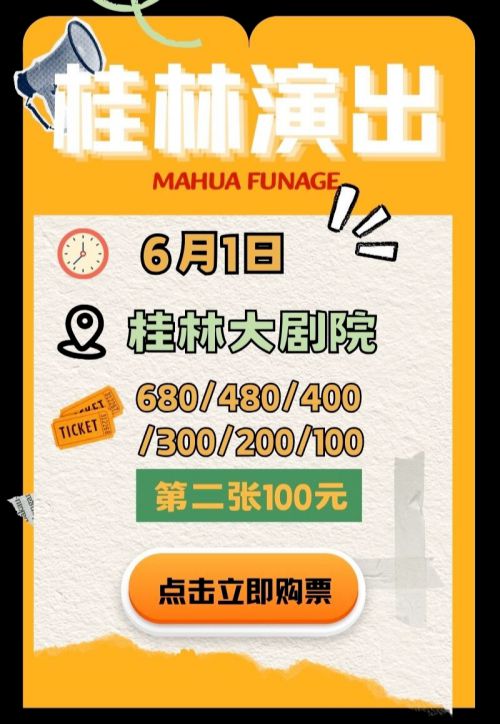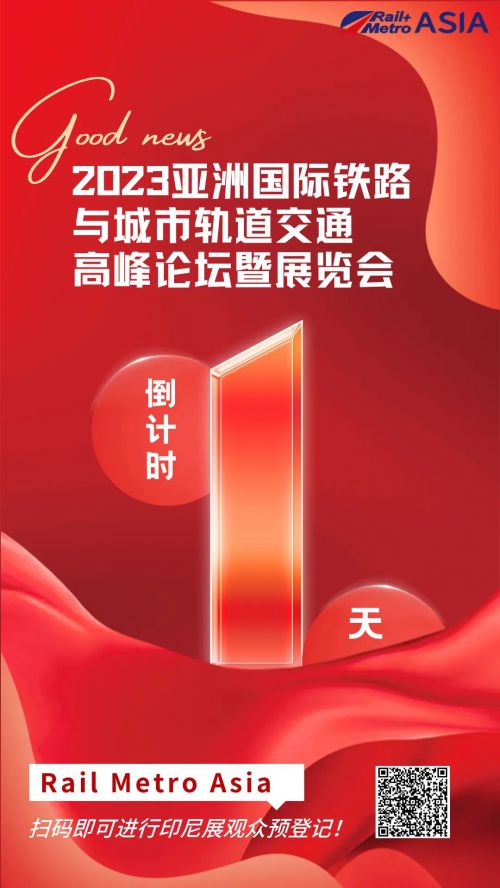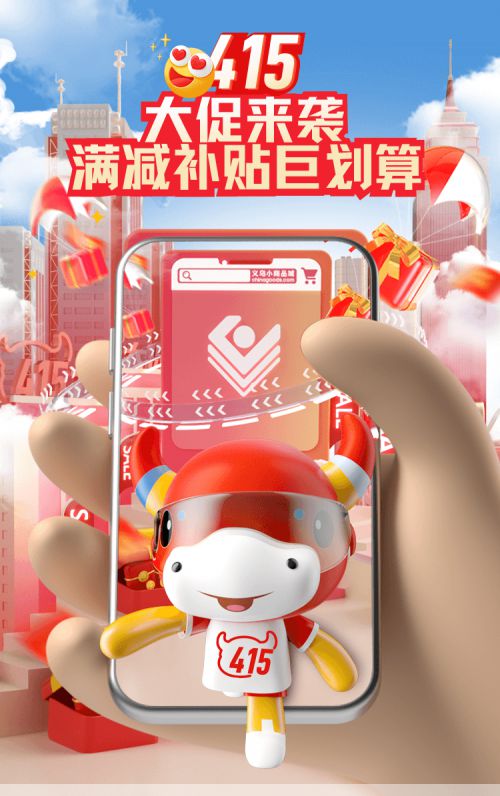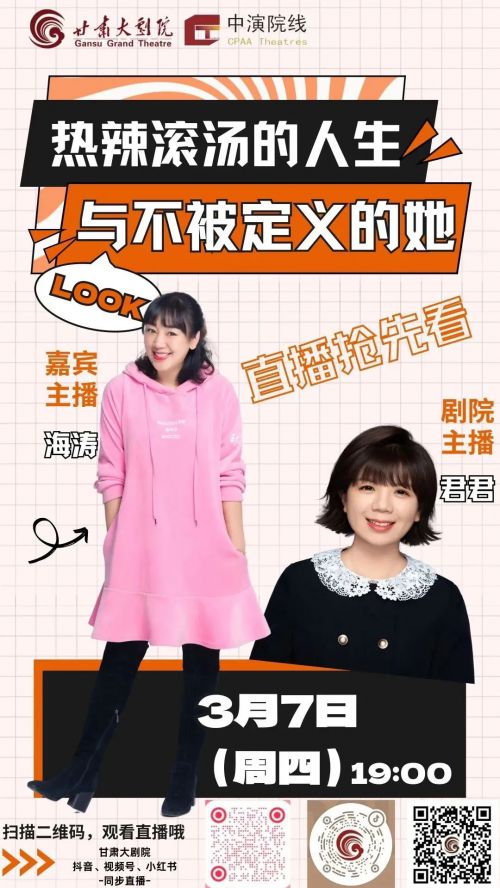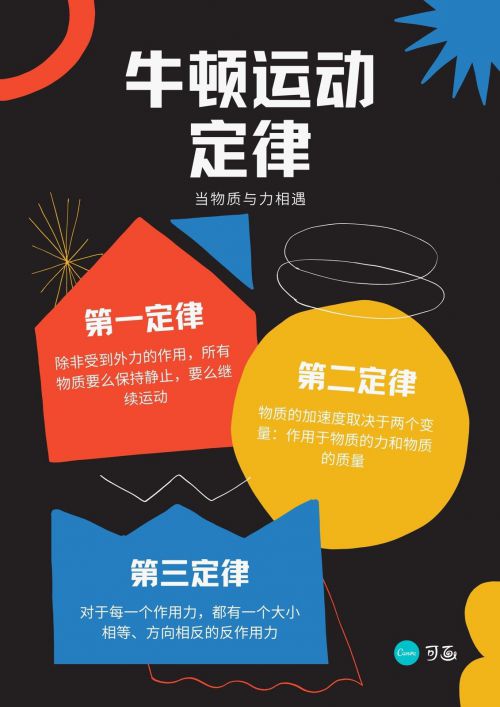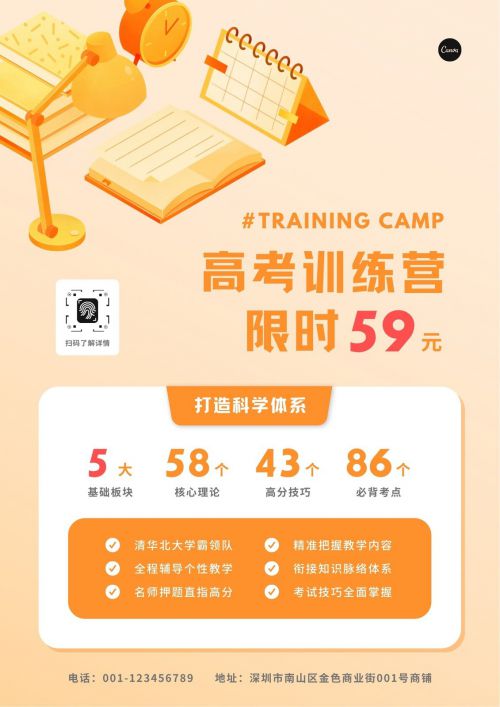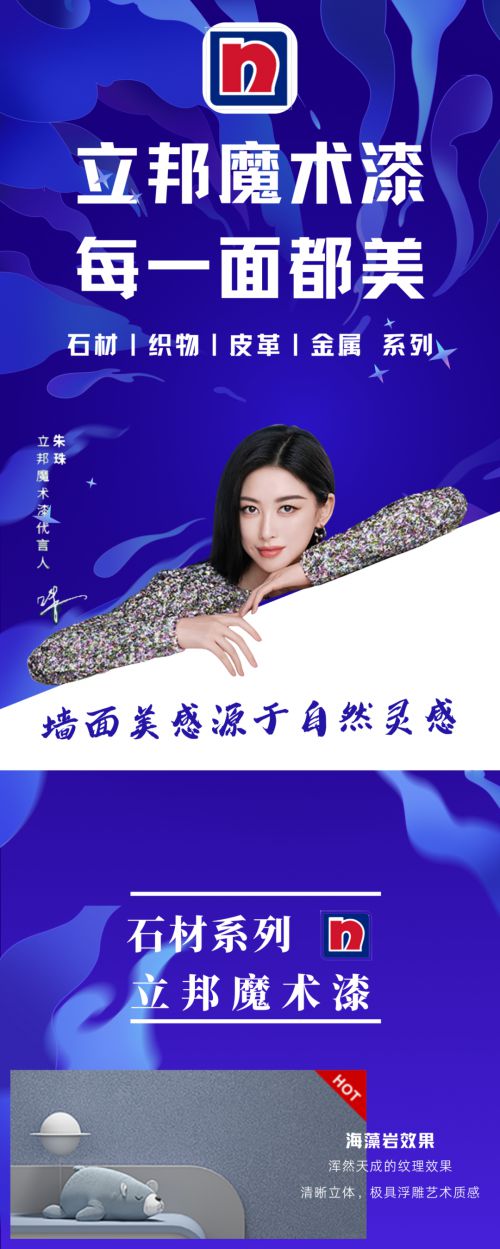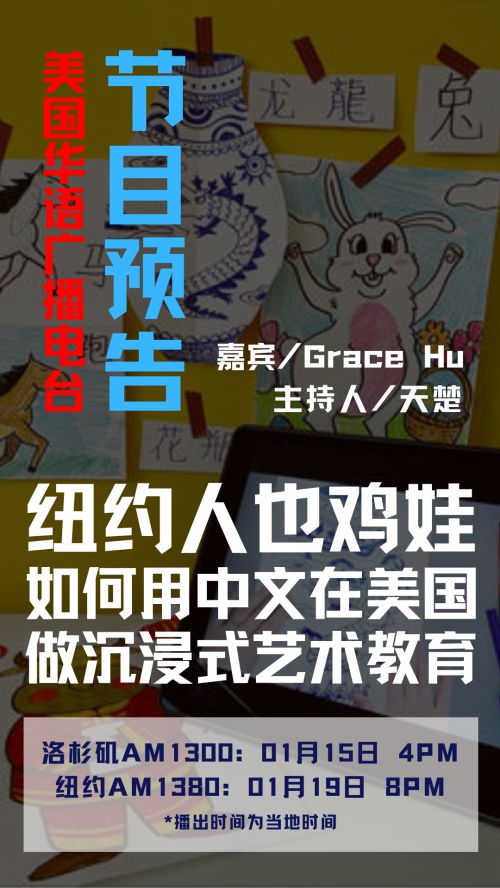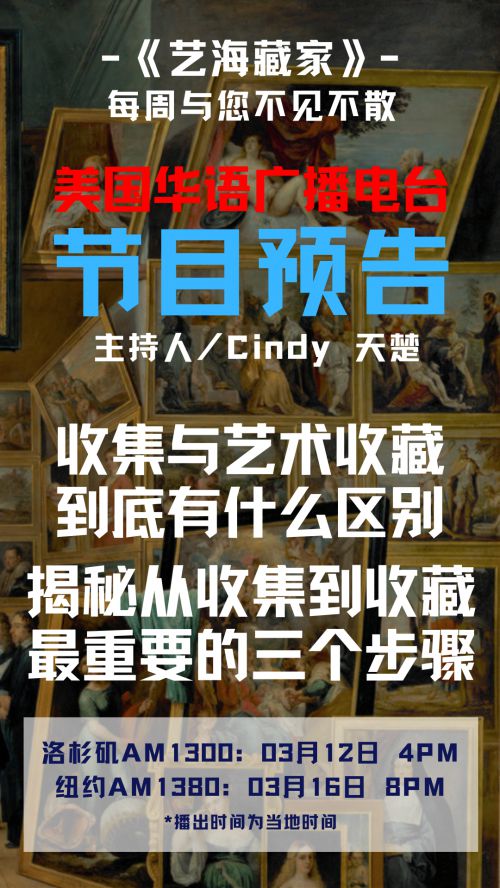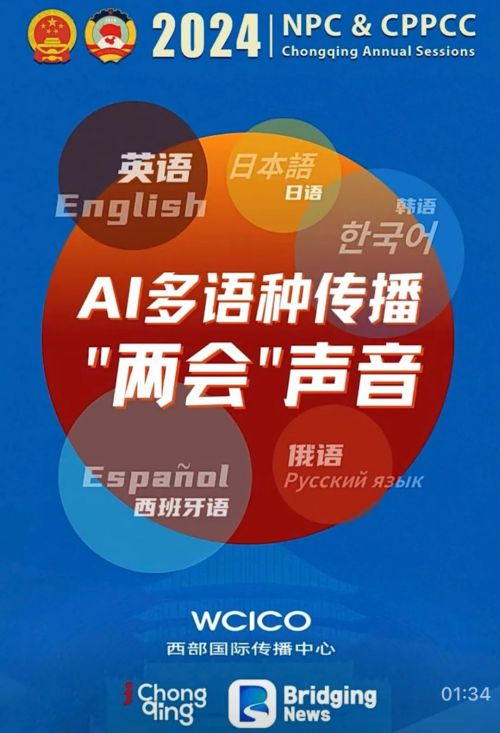
点字倔强黑是一款兼具力量感与现代美学的创意黑体,以方正饱满的字形、居中重心及宽博中宫构建出沉稳大气的视觉基底。粗重均匀的方头笔画搭配巧妙断开的连接设计,让字体在保持简约质感的同时,通过斜切笔锋与装饰元素的点缀,赋予点、提、撇、捺、勾等笔画独特张力——每一处细节处理都暗藏巧思,既保留黑体的经典骨架,又突破传统束缚,在酷劲外表下呈现鲜明个性。 作为多字重粗体字库,点字倔强黑适配多种现代创意场景:电商促销海报的吸睛标题、影视宣传物料的视觉焦点、潮流品牌的VI主视觉,皆能以其强大的视觉冲击力快速抢占受众目光。支持会员商用授权,满足从设计到商用的全链路需求,是传递力量态度与时尚美学的理想选择。